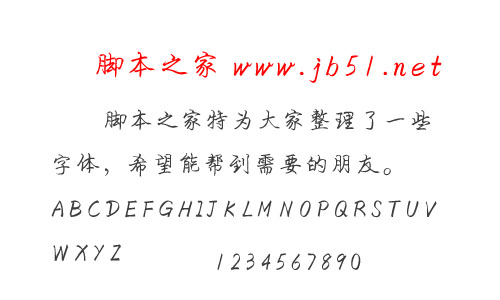
書香體字體是一款具有手寫風(fēng)格的書香體字體,該字體的原形是陳代明硬筆體,字體書寫流暢,瀟灑大方,特別適合喜歡書法的朋友在電腦上或手機(jī)上安裝使用,同時(shí)也可用于藝術(shù)設(shè)計(jì)、包裝印刷、簽名設(shè)計(jì)、圖形設(shè)計(jì)等領(lǐng)域,歡迎有喜歡的朋友前來下載。